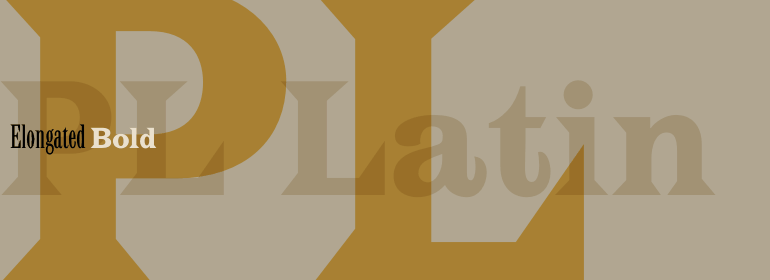
PL Latin
PL Latin,这款字体结构工整、笔画清晰,兼顾美观与易读性,适用于标题、正文、海报、包装、LOGO 等多种场景。字形优雅稳定,风格百搭耐看,适配日常排版与创意设计,让文字呈现更舒适、更具质感。PL Latin一笔一画,皆是细节,以均衡的比例、流畅的线条打造舒适视觉体验,字形端正大气,风格简约现代。无论是商业设计、品牌宣传还是日常排版,都能轻松驾驭,让文字更有格调与力量。PL Latin字体下载。